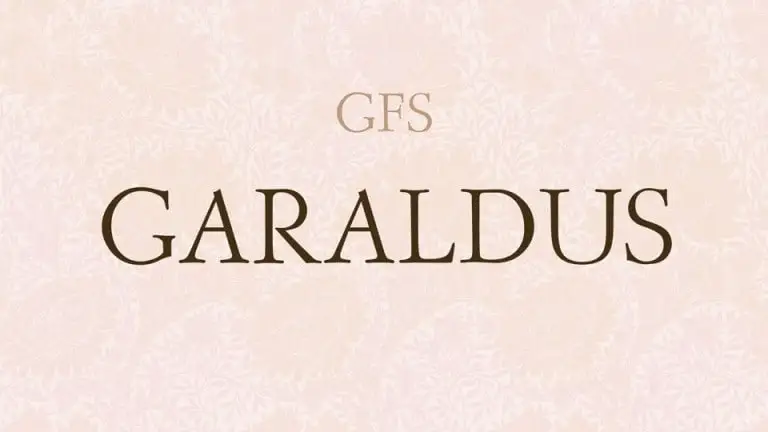
A GFS Garaldus Serif é uma fonte séria moderna que oferece uma experiência única para designers e profissionais de design gráfico na categoria de serif fonts. Ela surge de um designer chamado Greek Font Society, trazendo ao mercado um tipo clássico elegante e, simultaneamente, moderno. Inspirada nos tradicionais folhas venetais do século XVI, esta fonte é perfeitamente adequada para aplicativos que valorizam tanto a estética clássica quanto o toque contemporâneo. Suportando os idiomas latino-grego, a GFS Garaldus Serif permite uma ampla gama de aplicações em projetos de design gráfico. Ela é perfeita para criar um ambiente agradável e sofisticado nos seus trabalhos, com linhas elegantes que se movem de forma suave e harmoniosa ao longo dos caracteres. Seja para o design editorial, criação de logotipos ou qualquer aplicação onde você busca uma fonte séria e moderna, esta é uma escolha perfeita. Seja você um profissional de design gráfico ou um amante do design, a GFS Garaldus Serif oferece um elemento único que irá adicionar profundidade e beleza ao seu trabalho. Seja qual for o projeto, ela tem algo para oferecer em termos de estilo e funcionalidade.